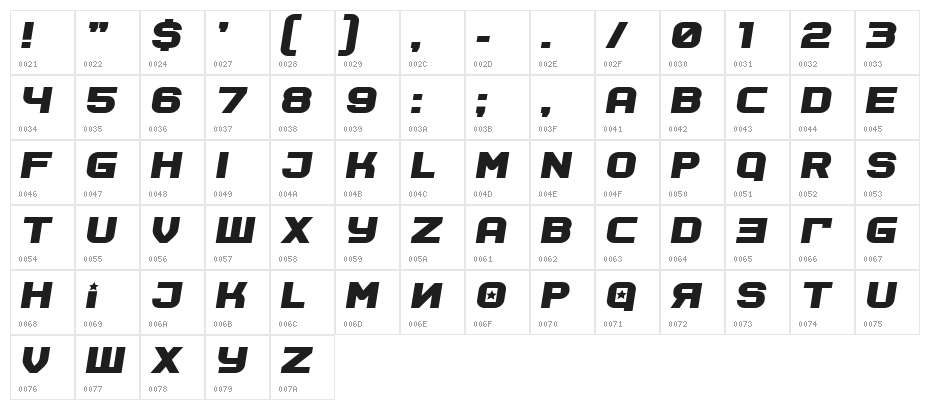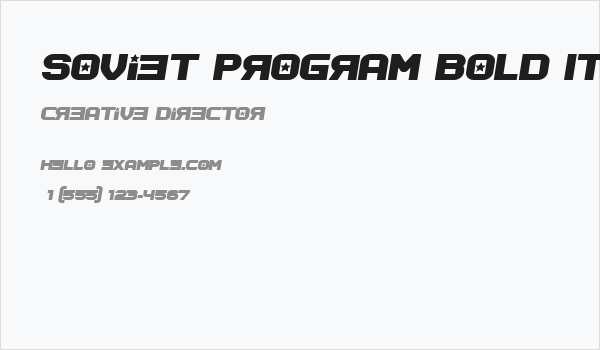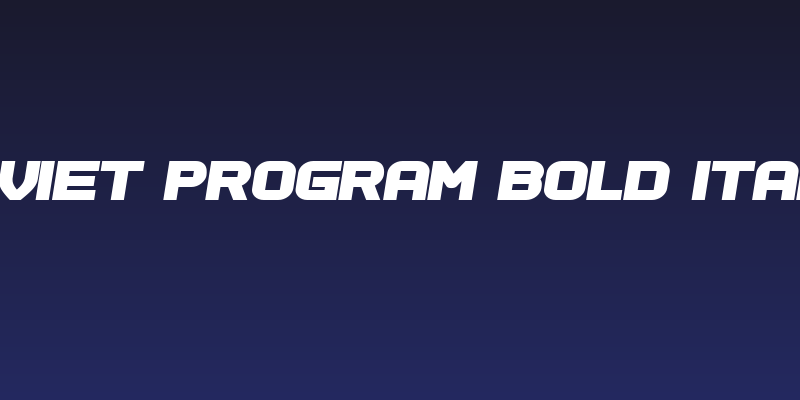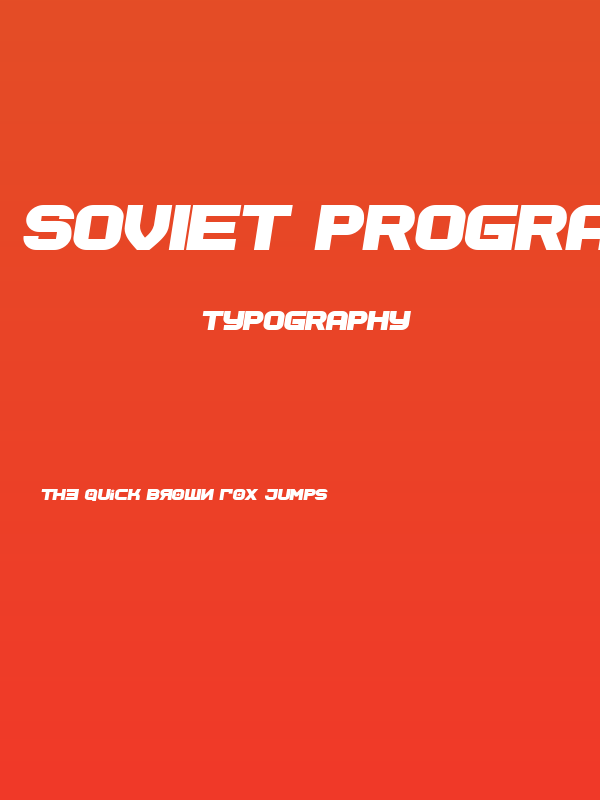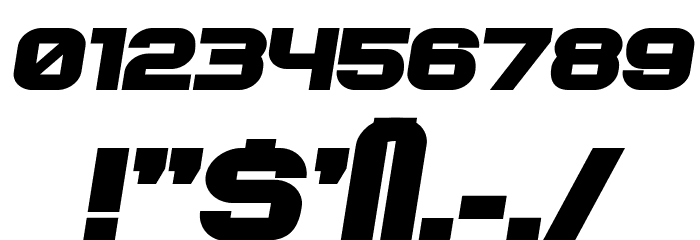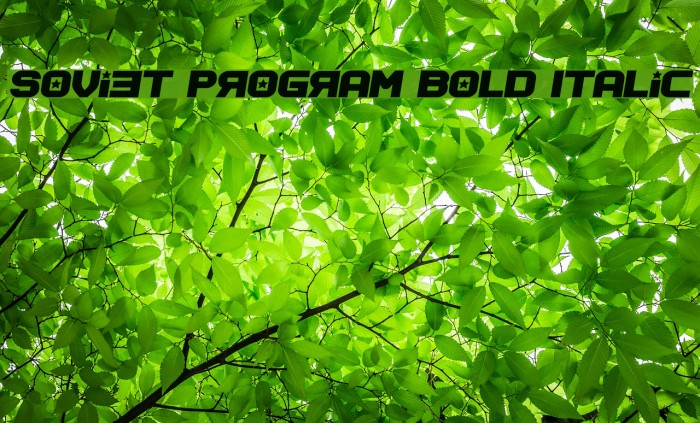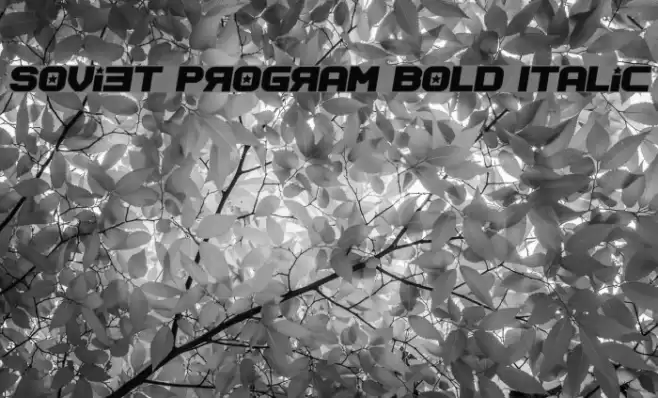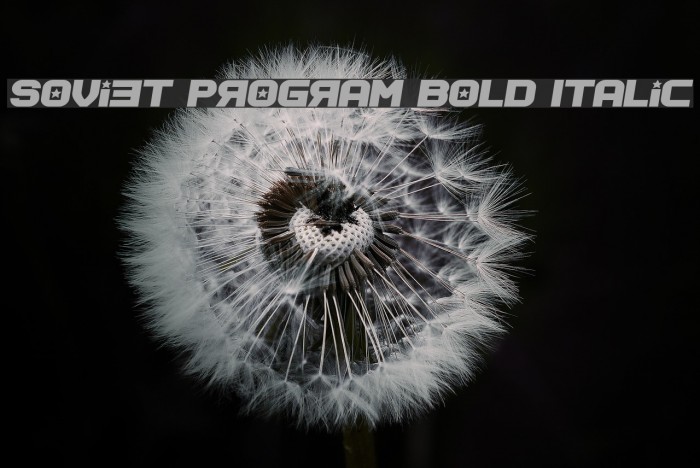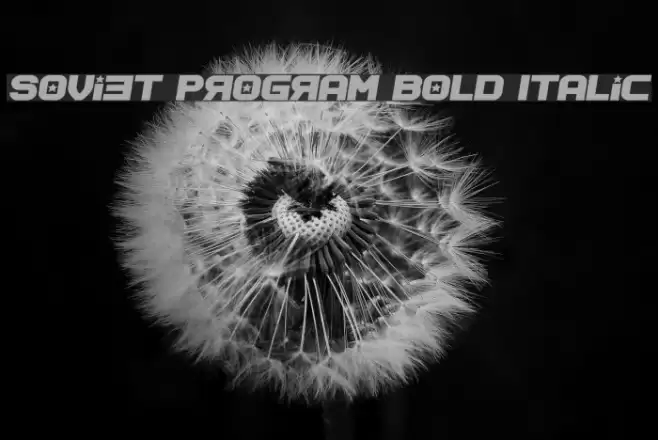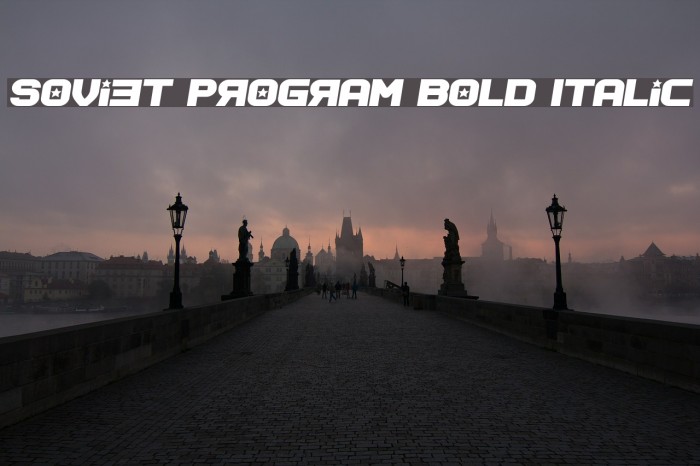
Soviet Program Bold Italic Font
Vladimir Nikolic - www.coroflot.com/vladimirnikolic
| Estilo general | Futuristic, Decorative |
| Proyectos propuestos | Ideal for sci-fi themed posters, video game titles, branding for tech companies, and any project requiring a modern, bold statement. |